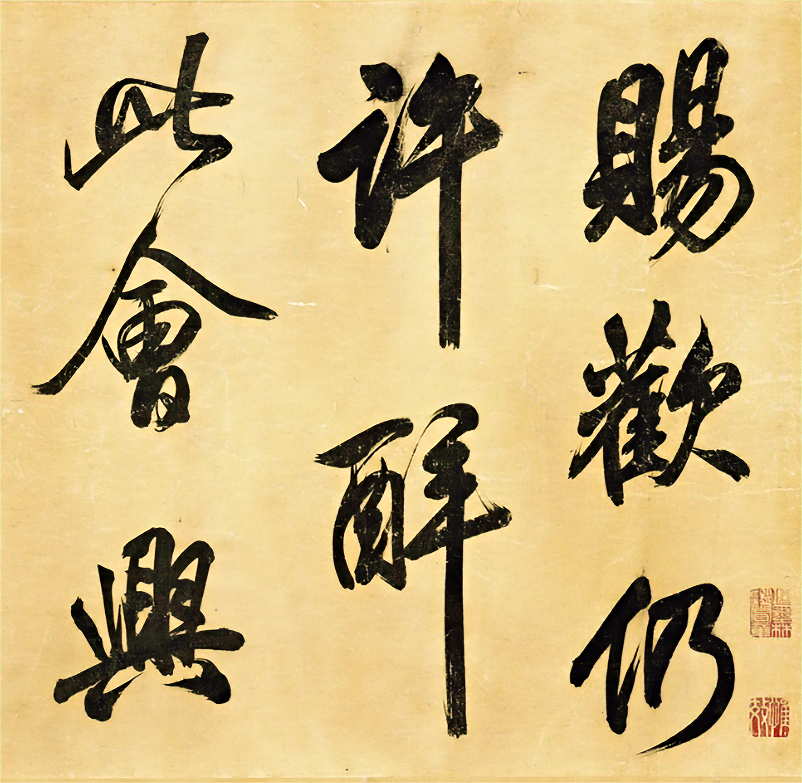
汉标米芾曲江宴会即事
关于汉标米芾曲江宴会即事字体字库信息
字体全名: 汉标米芾曲江宴会即事
铸字厂: 真迹小字库
字体简介: 下载须知:本字库非标准GB2312字库。本字库只包含了米芾《曲江宴会即事》真迹上的“76个字”。宋米芾书真蹟卷白居易上巳日恩赐曲江宴会即事,宋哲宗绍圣元年(1094),台北故宫博物院藏。
所属分类: 行楷毛笔字手写体书法